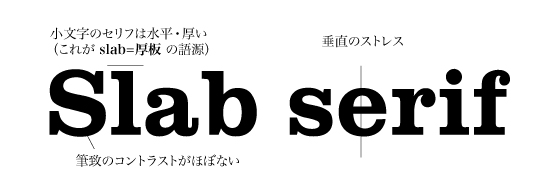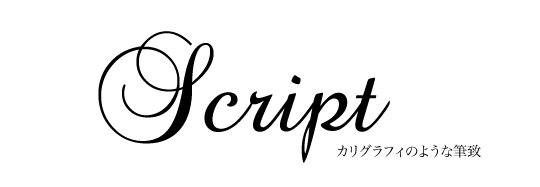
最低限知っておきたいフォントの基礎知識
はじめに
フォントは好きだけど、そう言えばフォントについて何も知らない… 今一度フォントの基本をおさえておきましょう。
「ノンデザイナーズ・デザインブック」で紹介されている区分を元に フォントの基礎知識をご紹介します。
oldstyle
オールドスタイルで作られた書体は、手書き文字をお手本にしています。 文字には必ずセリフ(文字のストロークの端にある小さな飾り)があります。小文字のセリフは必ず斜めになっています。(図参照)手書きのペンで書かれた文字であるために、文字の曲線部分には太い部分から細い部分への太さの推移があります。これを専門用語で「thick/thin transition」と呼びます。オールドスタイルにおいては、この筆致のコントラストは比較的穏やかです。曲線のもっとも細い部分同士を結んだ線をストレス(stress)と呼びます。オールドスタイルの活字は斜めのストレスをもっています。 オールドスタイルの書体は全て同じように見えます。 個性が強くないところがこの書体の個性なのです。文字そのものに注意を払う必要がないため、読み手はスムーズに文章を読むことが出来ます。ですから、長文の文章をレイアウトするときにはオールドスタイルの文字がおすすめです。 ・有名なオールドスタイル書体 -Garamond -Times New Roman -Goudy -Baskerville … 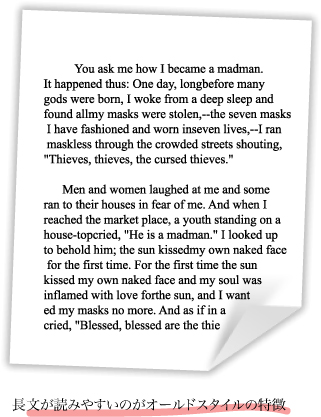
modern
髪型やファッションと同じように、活字にも流行があります。 1700年代、紙が以前よりもなめらかになり印刷技術も発展すると、よりいっそうメカニカルな活字が誕生しました。これがモダン文字です。先に紹介したオールドスタイルとは違って、モダン文字は手書きの文字を模倣していません。同じようにセリフがありますが、傾斜せず水平で不自然に細くなっています。また、ストレスはほぼ垂直です。太い部分は出来る限り太く、細い部分は出来る限り細く。強いコントラストを持ち、人目を引くのがこの文字の特徴です。 モダン書体は強い太さの推移(コントラスト)を持っているため、多量の文字を読ませるのには適しません。しかし、人工的でエレガントな雰囲気、与える印象の強さはこの字特有のもの。 用途を選べば読み手の目線を惹きつけることが出来るでしょう。 ・有名なモダン書体 -Bodoni -Times New Bold -Ultra -Walbaum ...
Slab serif
産業革命は広告という新しい概念をもたらしました。 初期の広告では先ほどのモダン書体の太い部分をさらに太めた書体が使われました。しかし、こうした文字は遠目に見ると太い部分しか目に入らず、読み取れません。ではどうしたらいいのでしょう?そう、文字全体を太くすれば良いのです。 こうして出来たのがスラブセリフです。 ですから、スラブセリフ書体には太さの推移をほとんどありません。 スラブセリフ書体は可読性に優れているので、本文部分に使うのにも適しています。しかし、文字が太く推移が少ない分、オールドスタイルで作られたページに比べると全体的に文章部分が目立つ暗めのページになります。出来あがりのイメージに合わせて書体を使い分けて下さい。 ・有名なスラブセリフ文字 -Clarendon -Memphis -Cairo -New Century Schoolbook ...
Sans serif
「sans」とはフランス語で「~がない」という意味です。サンセリフ書体にはその名の通り、セリフがありません。セリフをなくすという考え方は書体の進化のかなり後期に出てきたもので、20世紀に入るまではあまり市民権を得られませんでした。サンセリフ書体はほとんど必ずといっていいほど太さが一定で、コントラストを持ちません。
しかし中には例外もあります。膨大な数のあるサンセリフ書体には、ごくごく少数ですが、わずかな太さの推移を持つ書体があるのです。このような書体は、コントラストを持つ点で他のセリフのある書体に似ていますが、セリフを持たない点ではやはり一般的なサンセリフの書体にも似ています。 このため他の書体と組み合わせて使うのがとても難しいのが特徴です。 ・有名なサンセリフ書体 -Antique Olive -Franklin Gothic -Futura -Formata ...
script
スクリプト書体のカテゴリーには、装飾書体用のペンや筆、鉛筆、製図ペンで書いた文字のように見える書体が全て含まれます。このカテゴリーはさらにいくつかのグループに用意に分類することができます。つづけ字(英語の授業で習った筆記体です)のスクリプト書体、普通の手書き文字を真似た書体、カリグラフィーのような書体などなど。 スクリプト書体は強いインパクトを持ちます。使いすぎるとしつこい印象を与えるので、要所要所で使うのがおすすめです。ここぞ!というタイミングで思いきって大きなサイズで使うと、目覚ましい効果を発揮します。 フリーフォントでも使いやすいスクリプト書体が沢山あるので、是非お気に入りを探してみてください。 ・有名なスクリプト書体 -arid -linoscript -zapf chancery -legacy ...
decorative
前述したどのカテゴリーにも属さず、本文全体がその書体で組んであったら読みたくなくなるような書体はたいていデコラティブ書体に分類できます。デコラティブ書体は目立ちます。目立ち、楽しく、使いやすく、大抵の場合値段も安い(あるいは無料)です。何か風変わりなアイディアを表現したいとき、必ず手助けとなるでしょう。 例えばくだけた雰囲気を感じる書体をあえて格式ばった場面で使ったらどうなるでしょうか。おどろおどろしい文字を愉快な文章に使ったらどのような印象を与えるでしょうか。デコラティブ書体は使い方次第で、明白な感情をまっすぐに伝えることも、あえて異なる意味合いをひねって伝えることもできます。使いすぎに注意しつつ、沢山の可能性を試してみてください。